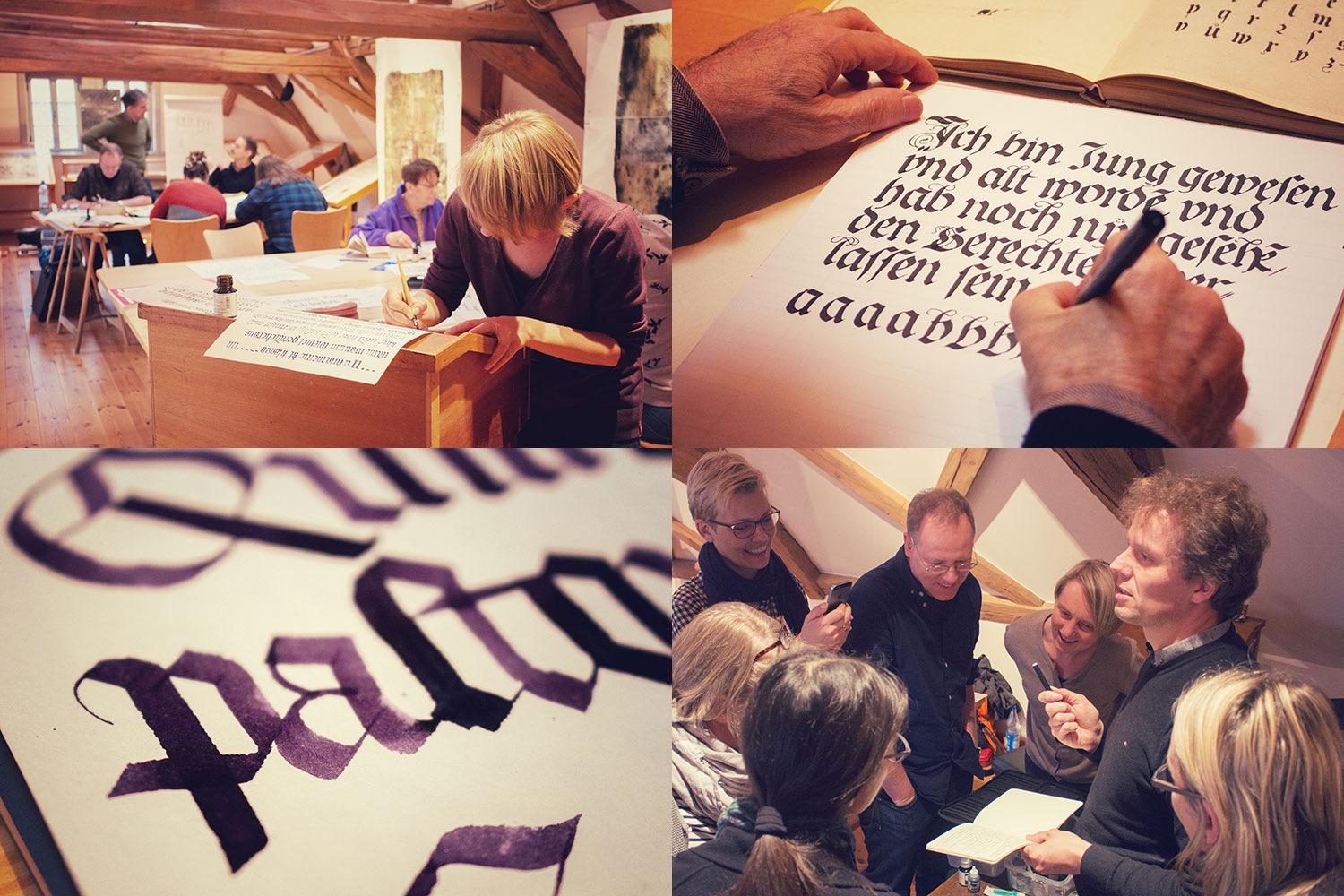
Kalligrafie-Kurs: Von Textura zur Fraktur (ausverkauft)
Ein Kalligrafie-Wochenend-Workshop für gebrochene Schriften mit Tobias-David Albert.
Der Wochend-Workshop knüpft an den ersten Teil des Workshops an. Trotzdem ist er ein offenes Angebot an jeden Menschen, der etwas Erfahrung mit Kalligrafie oder Typografie mitbringt. Die Textura stellt den Ausganspunkt für gebrochene Schriften im Mittelalter dar. Mit der Fraktur erreichen diese Schriftformen ihren Höhepunkt im 15. Jahrhundert. Hier wird der Strich der gebrochenen Schriften beweglicher und spielerischer und formt so einen neuen Typus von Handschrift. Vor allem die Versalien der Fraktur-Schriften laden zum experimentieren und spielen ein. Anhand von Schreibvorlagen wird mit Rohrfedern, Paralell-Pen und anderen Schreibgeräten gearbeitet. Dazu gibt es Hintergrundwissen zur Beziehung von gebrochenen Schriften zur Antiqua. Das wiederum führt auch zu einem bessseren Verständnis der Formen, der heute gebräuchlichen Buchschriften in der Typografie – oder macht einfach Spaß zu entdecken. Große, kleine, kuriose und moderne Werkzeuge, Tinten, Papier und weiterführende Literatur werden vorgestellt.